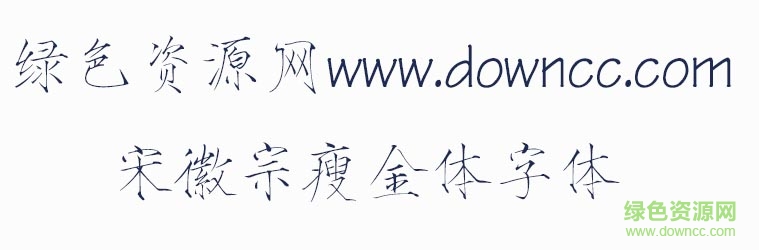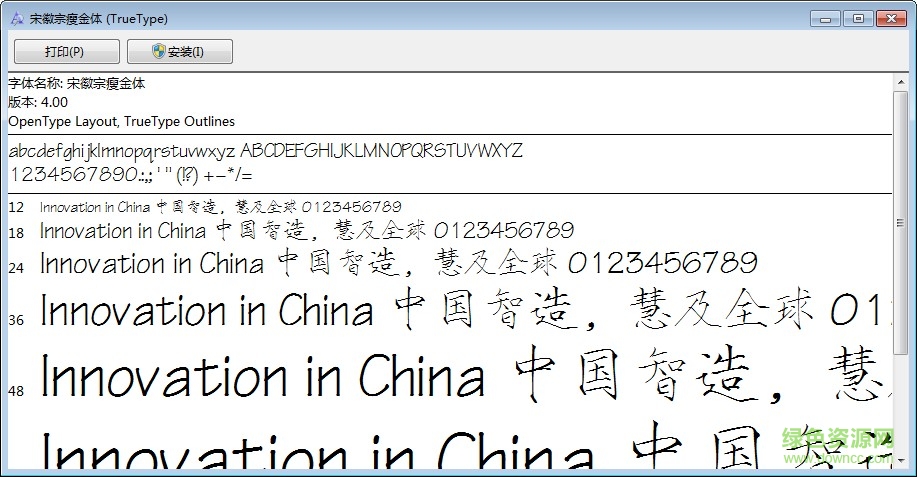
宋徽宗瘦金體字體是一款最正宗的瘦金字體,該字體棱角分明,整體效果十分大氣,能夠滿足產(chǎn)品包裝、廣告宣傳、出版印刷、商標(biāo)用字、商業(yè)網(wǎng)站、影視影像視頻、書籍出版印刷等,有需要的朋友可以免費(fèi)下載收藏。
瘦金體為宋徽宗趙佶所創(chuàng),是書法史上極具個(gè)性的一種楷書書體,因其與晉楷唐楷等傳統(tǒng)楷書區(qū)別較大,個(gè)性極為強(qiáng)烈,故可稱作是書法史上的一個(gè)獨(dú)創(chuàng)。
瘦金體運(yùn)筆靈動(dòng)快捷,筆跡瘦勁,至瘦而不失其肉,其大字尤可見風(fēng)姿綽約處。因其筆畫相對(duì)瘦硬,故筆法外露,可明顯見到運(yùn)轉(zhuǎn)提頓等運(yùn)筆痕跡,是一種風(fēng)格相當(dāng)獨(dú)特的字體。